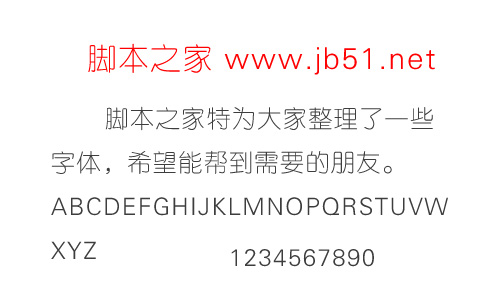
方正细圆简体字体
方正细圆简体字体是方正字体库中的一种字体,方正圆体家族的中宫宽松,字面大,起笔处与收笔处为圆形,折笔处呈圆弧状。方正圆体家族的字形风格舒展柔和,适用于女性、儿童和生活用品类的宣传册和包装设计等。方正圆体家族包括3款字重,其中方正粗圆笔画厚重饱满,适用于标题;方正准圆笔画粗细适中,适用于正文排版;方正细圆笔画纤柔,也适用于正文排版。喜欢的朋友们可以前来下载使用。